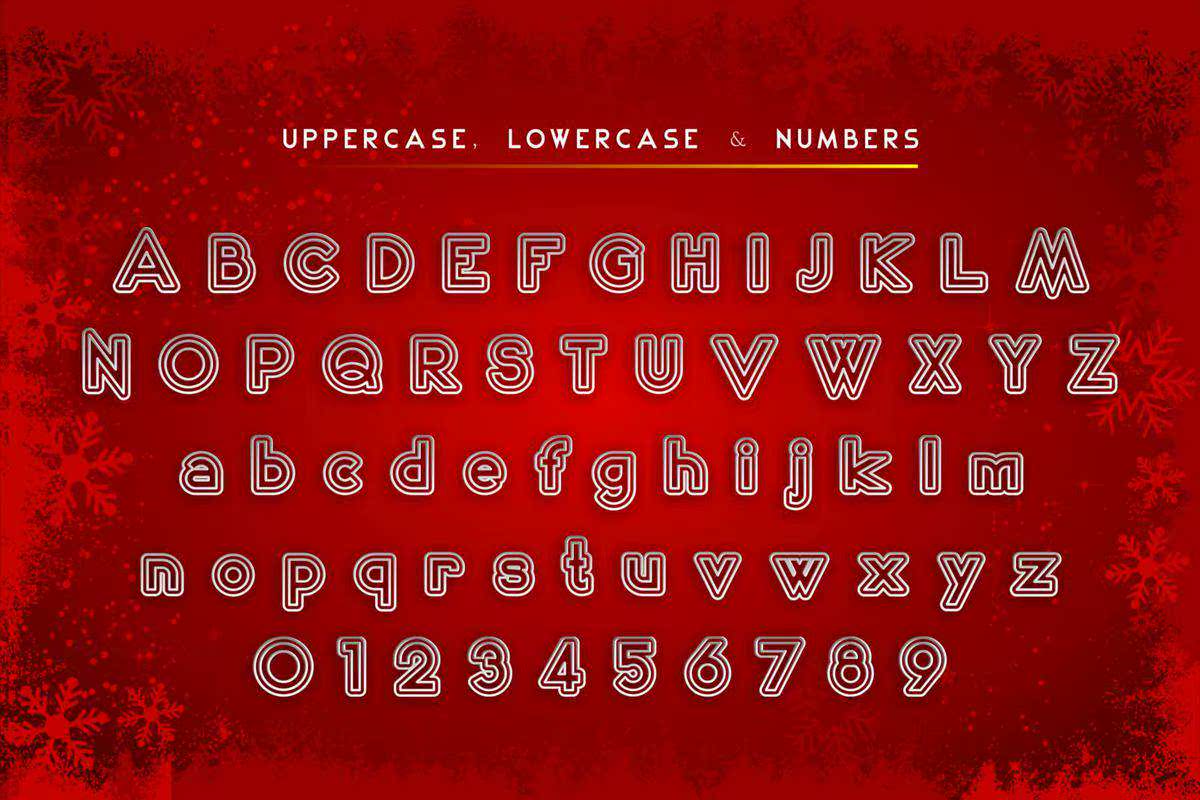
2020大纲视图显示是您的新年项目的完美选择。在2020年新年和冬季之前的一个全新的外观,是本年度“SamazignewyearProject”的完美选择。它在许多方面都是完美的!2020大纲视图显示是您的新年项目的完美选择。在2020年新年和冬季之前的一个全新的外观,是本年度“SamazignewyearProject”的完美选择。它在许多方面都是完美的!